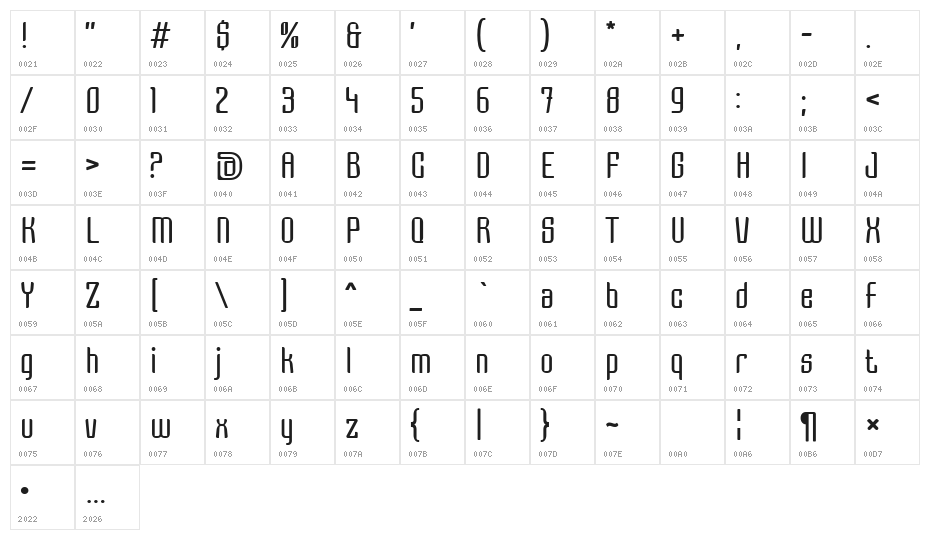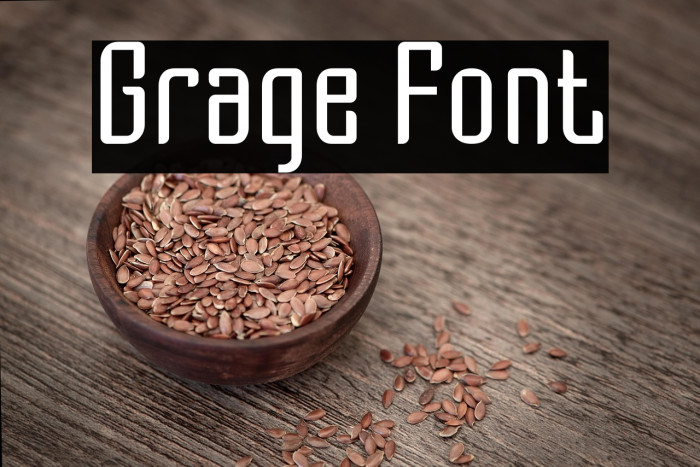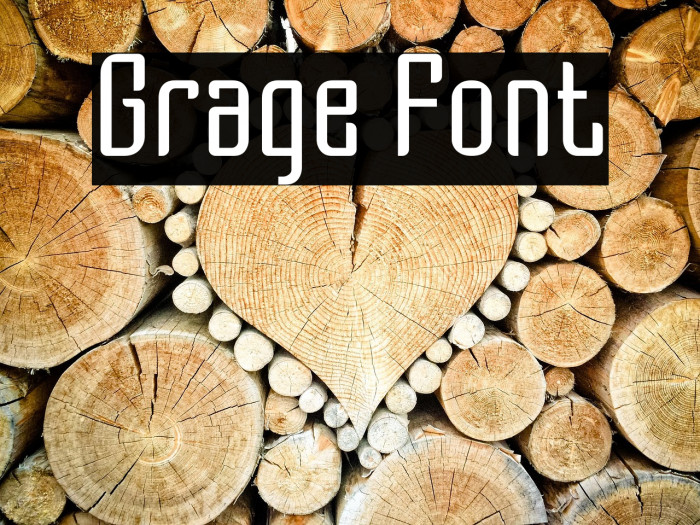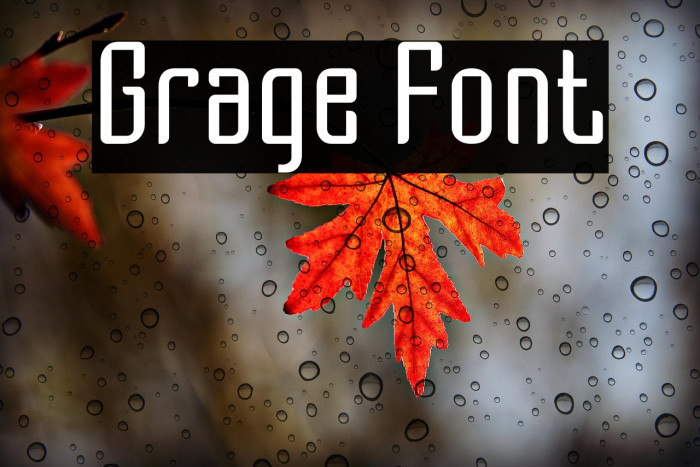
Grage Font
| Anwendungsfall | Headlines, Logos, Digital Interfaces |
| Vorgeschlagene Projekte | Ideal for branding, packaging, and digital interfaces where a modern and clean aesthetic is desired. |